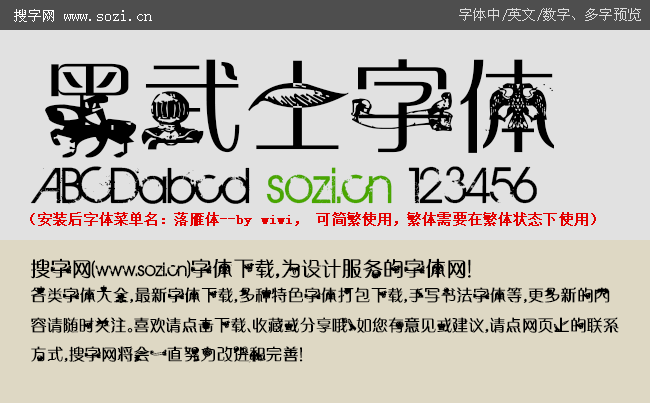
黑武士字體
搜字網(wǎng)給大家提供一款很卡通的手機(jī)中文字體下載。修改者給這款字體叫黑武士字體,這款手機(jī)中文字體以倩體為原形,在筆畫(huà)間嵌入了大量的卡通圖形,該中文字體趣味性強(qiáng),又保持了文字的識(shí)別度,非常適合喜歡卡通的朋友在手機(jī)上安裝使用。